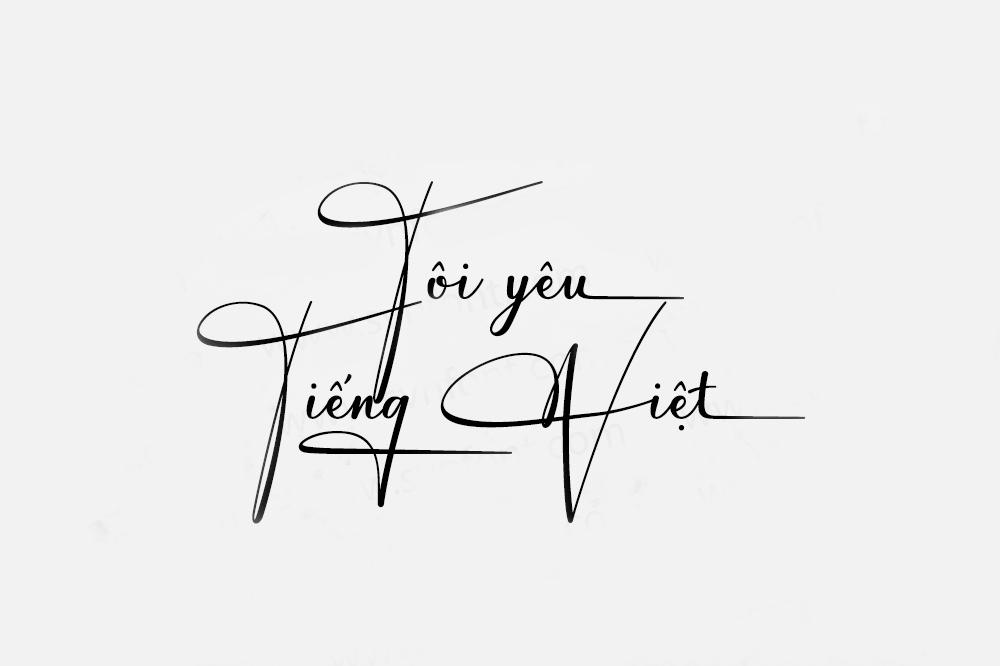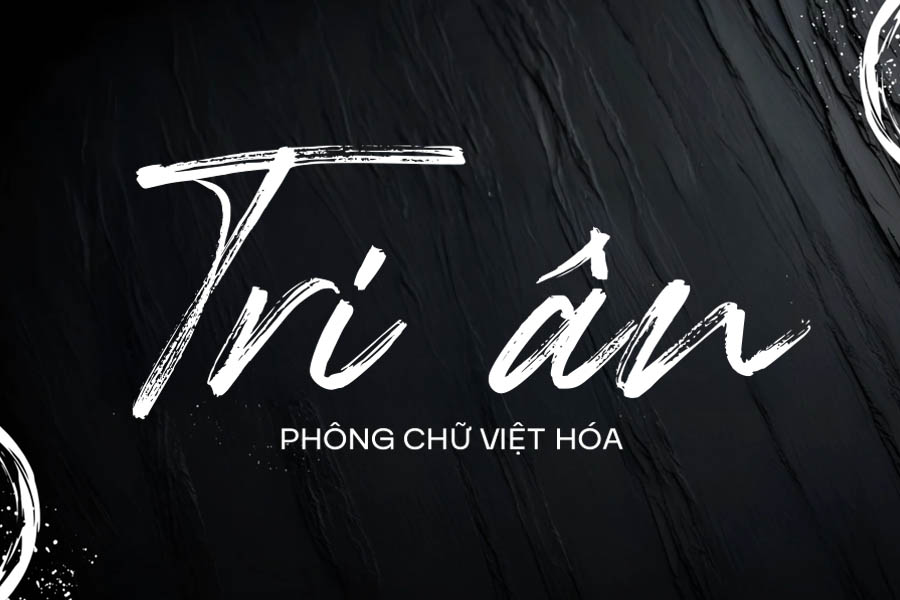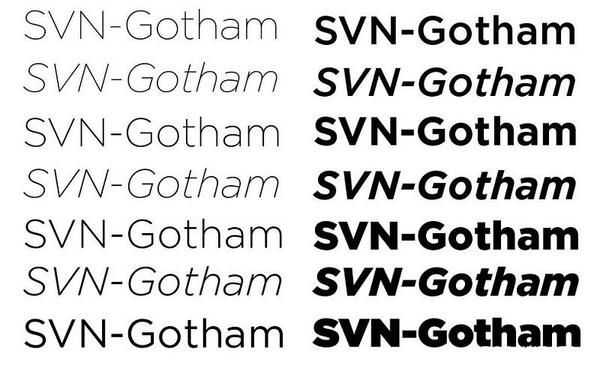
Tải font SVN (Style Việt hóa) là nhu cầu hàng đầu của giới thiết kế tại Việt Nam khi cần một bộ sưu tập phông chữ đa dạng, hiện đại và hỗ trợ tiếng Việt hoàn hảo. Khác với các bộ font gốc nước ngoài thường xuyên bị lỗi nhảy dấu hoặc sai lệch khoảng cách ký tự, việc download font SVN Việt hóa giúp bạn sở hữu hệ sinh thái Typography chỉn chu cho cả thiết kế số và in ấn thực tế. Doozypack.vn cung cấp link tải bộ font SVN trọn gói, giúp bạn giải quyết triệt để vấn đề lỗi font và nâng tầm thẩm mỹ cho mọi ấn phẩm bao bì.
Bộ font SVN là gì? Tại sao designer luôn ưu tiên sử dụng?
Font SVN là những phông chữ nổi tiếng thế giới được đội ngũ Style Việt hóa tinh chỉnh lại hệ thống dấu thanh (ă, â, đ, ê, ô, ơ, ư) để tương thích hoàn toàn với bảng mã Unicode phổ biến tại Việt Nam.
Bộ font SVN đa phong cách
Giải quyết triệt để lỗi nhảy dấu tiếng Việt
Nỗi đau lớn nhất của designer là tìm được font chữ đẹp trên các trang quốc tế nhưng khi gõ tiếng Việt lại bị lỗi hiển thị ô vuông hoặc dấu thanh bị đè nét. Việc tải font SVN Việt hóa giúp loại bỏ hoàn toàn rủi ro này. Từng dấu sắc, huyền, hỏi, ngã, nặng được đặt ở vị trí cân đối, hài hòa với cấu trúc chữ gốc, đảm bảo tính chuyên nghiệp tuyệt đối khi đưa file vào sản xuất tại xưởng in.
Hệ sinh thái phông chữ dẫn đầu xu hướng
Hệ thống font SVN không chỉ tập trung vào số lượng mà còn chú trọng vào chất lượng thiết kế. Khi thực hiện download font SVN, bạn sẽ tiếp cận được các dòng Sans-serif thanh lịch, Serif quý phái và cả những dòng Script nghệ thuật đang thống trị ngành đồ họa toàn cầu.
Top các bộ font SVN được tìm kiếm nhiều nhất tại Doozypack.vn
Dưới đây là những “cái tên vàng” trong làng Typography thường xuyên xuất hiện trên các mẫu thiết kế bao bì cao cấp:
Font SVN Gilroy – Đẳng cấp Sans-serif hiện đại
Việc tải font SVN Gilroy là giải pháp hoàn hảo cho những thương hiệu theo đuổi phong cách tối giản và tinh tế. Với cấu trúc hình học chuẩn xác, Gilroy mang lại cảm giác minh bạch, uy tín, cực kỳ phù hợp cho thiết kế logo công nghệ, mỹ phẩm hoặc bao bì thực phẩm sạch. Nhiều designer chọn download font Gilroy vì khả năng hiển thị sắc nét đáng kinh ngạc từ màn hình điện thoại đến các tấm biển hiệu khổ lớn.
Font SVN Gotham – Sự vững chãi và chuyên nghiệp
Nếu bạn cần sự vững chãi, tải font SVN Gotham là lựa chọn không thể bỏ qua. Đây là bộ font mang hơi hướng đô thị mạnh mẽ, thường được các tập đoàn lớn lựa chọn để khẳng định vị thế thương hiệu trên các ấn phẩm báo cáo năng lực hoặc túi giấy doanh nghiệp.
Font SVN Yipes – Phá cách cho tiêu đề nghệ thuật
Với những dự án cần sự nổi bật và sáng tạo, tải font SVN Yipes sẽ mang lại diện mạo đầy cá tính. Những đường nét ngẫu hứng của Yipes rất phù hợp làm tiêu đề cho các chương trình sự kiện, bìa sách hoặc tem nhãn sản phẩm dành cho giới trẻ.
Mẫu chữ SVN đẹp
• Túi giấy thời trang: Sử dụng font Gotham hoặc Gilroy Bold giúp tên cửa hàng hiển thị vững chãi, hiện đại và dễ nhận diện từ xa.
• Tem nhãn decal: Các dòng font SVN được tinh chỉnh dấu chỉn chu giúp các thông tin hướng dẫn sử dụng ở kích thước nhỏ vẫn cực kỳ rõ nét và dễ đọc.
Kiểu chữ Việt hóa ấn tượng
03 Lưu ý kỹ thuật khi sử dụng font SVN cho file in thực tế
Để bản thiết kế đạt độ hoàn hảo nhất khi sản xuất thực tế tại Doozypack.vn, designer cần lưu ý một số vấn đề kỹ thuật:
• Quy tắc Convert Font: Đây là bước bắt buộc. Trước khi gửi file in cuối cùng đến Doozypack.vn, hãy luôn lệnh Create Outlines (Ctrl+Shift+O) cho toàn bộ nội dung chữ để tránh lỗi mất font hoặc nhảy dấu trên hệ thống máy in công nghiệp.